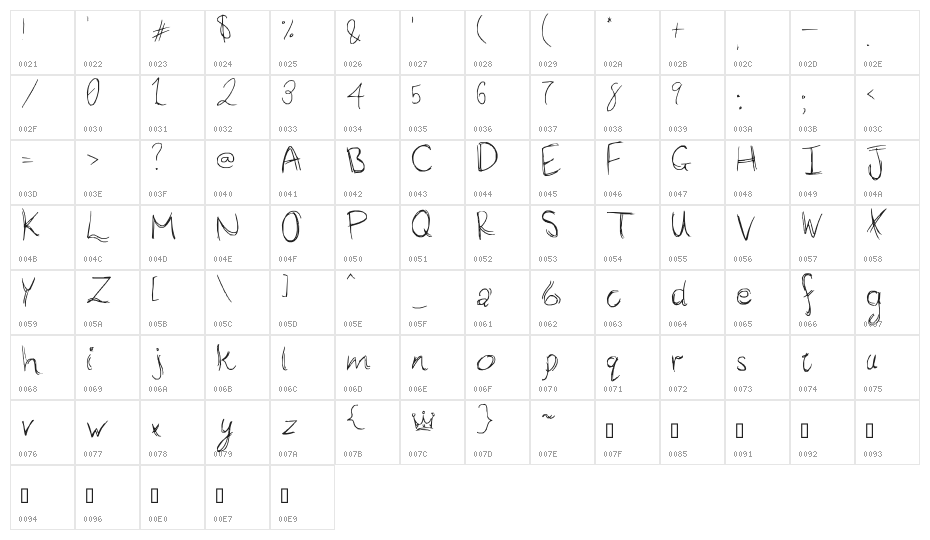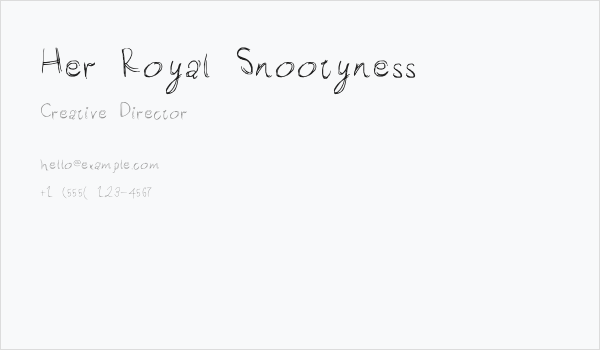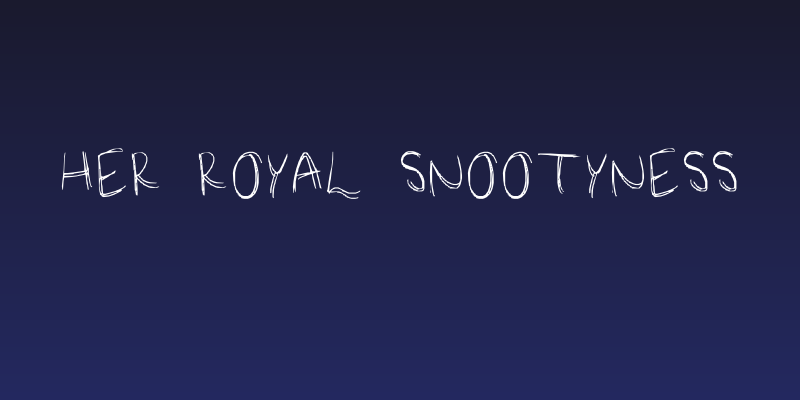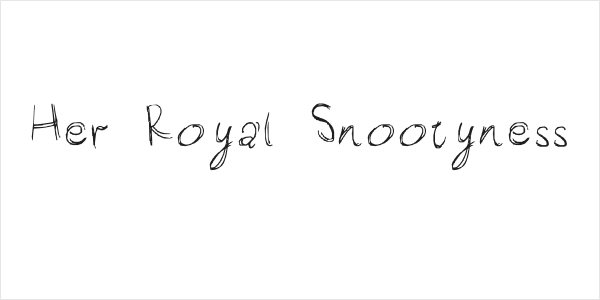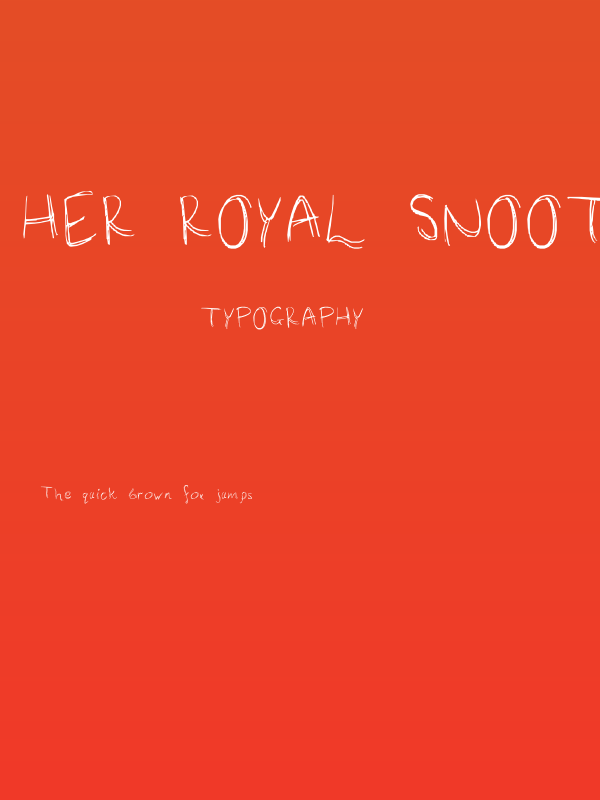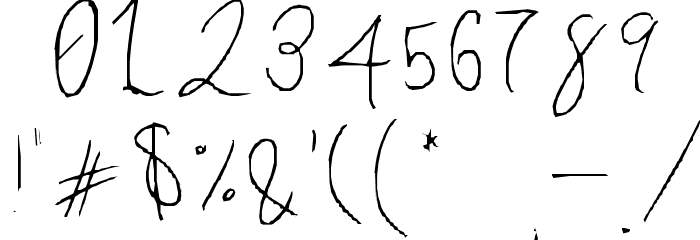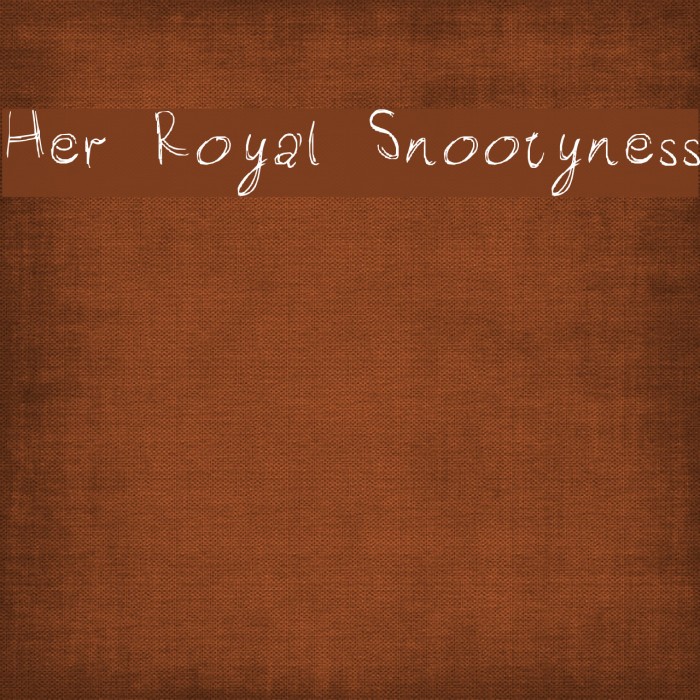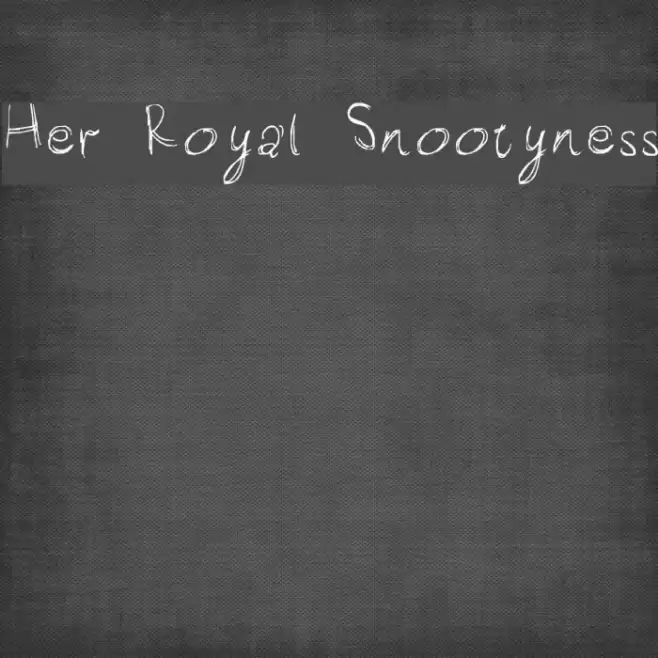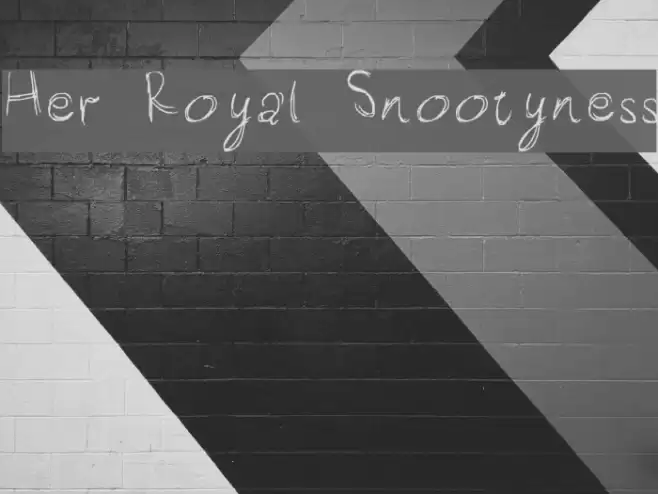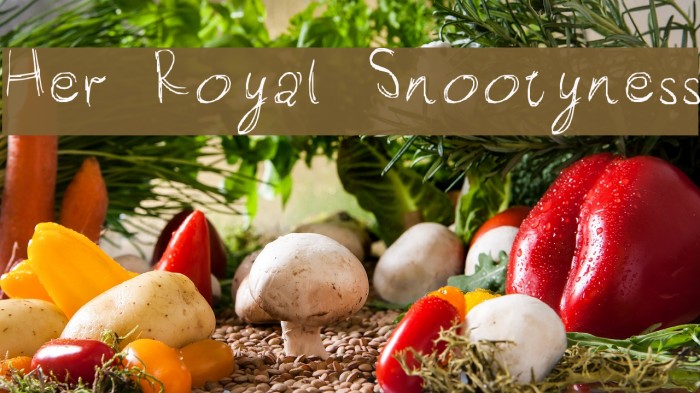
Her Royal Snootyness Font
| Cas d'utilisation | Logos, Posters, Creative projects |
| Projets proposés | Ideal for creative projects such as greeting cards, children's books, playful branding, and artistic posters. |